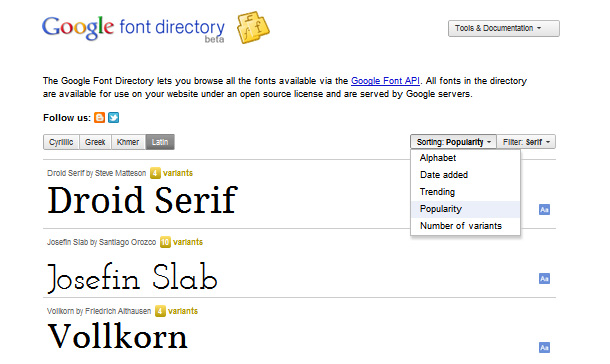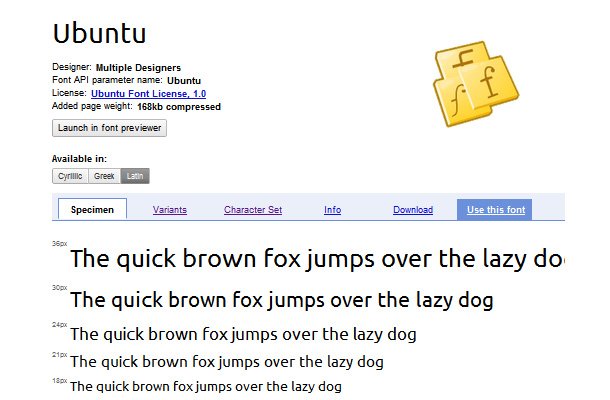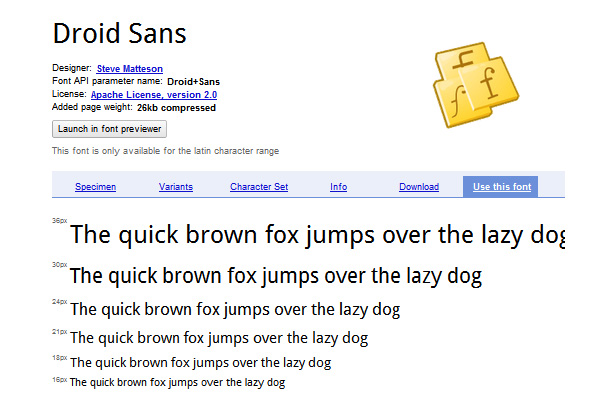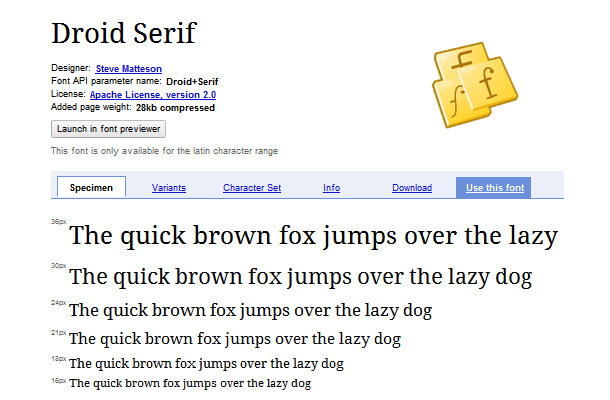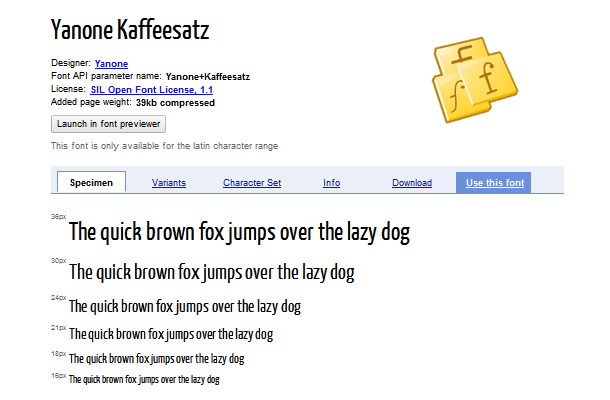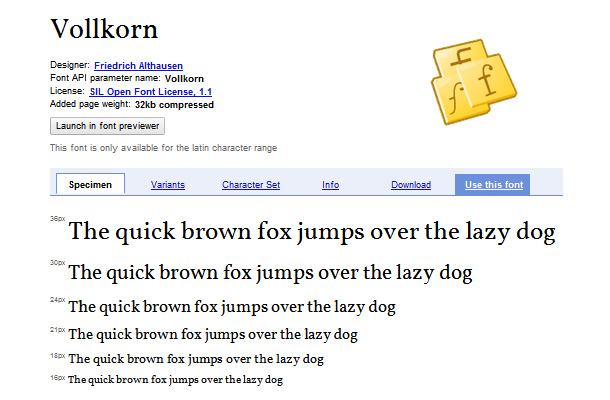
Die Google Web Fonts: Beliebte Schriften und praktische Tipps
Die Entwicklung der kostenlosen Web Fonts von Google geht schnell voran, und im Dezember sind noch einmal über 20 neue Schriften ins Font-Directory aufgenommen worden. Darunter einige sehr hochwertige Free-Fonts, z.B. die Ubuntu-Schriftfamilie. Und neben den neuen Schriften sind seit unserem letzten Artikel „Die kostenlosen Web Fonts der Google Font API nutzen“ auch noch einige neue Funktionen zum Sortieren der Schriften im Directory dazu gekommen. Zeit also für ein Update zu den praktischen Google Fonts.
1. Was sind Google Web Fonts?
Mit den Google Web Fonts hast du die Möglichkeit eine ganze Reihe von Schriften auf deiner Webseite zu nutzen, ohne dass du diese auf deinen eigenen Server hochladen oder über ein @font-face Kit (z.B. von Fontsquirrel) selbst aufwendig einbinden musst.
Du musst lediglich, die für dein Design benötigten Schriften und Schriftstile über einen Code-Schnipsel einbinden (hier die Erklärung zur Verwendung der Google Fonts). Sobald deine Webseite aufgerufen wird, werden die Schriften dann über den Google-Server geladen. Mit Hilfe des von Google und Typekit (dem derzeit größten Anbieter einer kostenpflichtigen Web Font Library) entwickelten Web Font Loader (einer JavaScript-Bibliothek) kannst das Ladeverhalten deiner Schriften sogar noch gezielter beeinflussen.
Ein großer Vorteil von Web Fonts, besonders im Vergleich zur Verwendung von Images, ist die so verbesserte Ladezeit. Außerdem können mit den Web Fonts eine viel breitere Vielzahl von Schriften unkompliziert genutzt werden, und auch moderne CSS3-Eigenschaften (wie text-shadow oder gradients) können verwendet werden.
2. Neue Features im Google Font Directory
Um die Schriften im Google Font Directory zu sortieren, gibt es inzwischen die neuen, praktischen Filter-Optionen.
Du kannst die Schriften zum einen nach den Schriftklassen Serif, Sans-serif, Display (dekorative Fonts, besonders für Logos oder Überschriften geeignet) und Handwriting filtern.
Daneben gibt es noch die Möglichkeiten die Web Fonts alphabetisch, nach Einstellungsdatum, Trend, Beliebtheit und Anzahl von Schrift-Varianten zu sortieren.
Eine zusätzliche Option ist das Filtern nach kyrillischen, griechischen, Khmer und lateinischen Schriften. Mit einem kleinen, blauen Symbol in der Schriften-Liste sind die zur Verfügung stehenden Schriften auch noch einmal markiert.
3. Die beliebtesten Google Web Fonts vorgestellt
Inzwischen sind schon eine ganze Reihe Web Fonts im Google Font Directory eingestellt. Daher möchte ich die beliebtesten Font hier etwas genauer vorstellen.
Ubuntu
– Die kostenlose Font-Familie des Open Source Betrieb-Systems Ubuntu.
Auch auf der Ubuntu-Webseite gibt es die Ubuntu-Schrift im Einsatz zu sehen.
The typeface is sans-serif, uses OpenType features and is manually hinted for clarity on desktop and mobile computing screens.
Ubuntu Font Family, Canonical und Dalton Maag
Seit Dezember 2010 kannst du auch die Ubuntu Schrift-Familie über die Google Font API nutzen. Ubuntu ist in den vier Varianten normal, italic, bold und bold italic verfügbar.
Droid Sans
– Eine beliebte serifenlose, fürs Web optimierte Schrift von Steve Matteson.
Droid Sans was designed with an upright stress, open forms and a neutral, yet friendly appearance.
Steve Matteson, Ascender Corp., in der Schriftbeschreibung von Droid Sans
Droid Sans ist die derzeit beliebteste Schrift der Google Web Fonts. Du kannst die Schrift in den Varianten normal und bold nutzen. Droid Sans ist extra für die Verwendung im Web entwickelt worden, und eignet sich besonders gut für Fließtexte.
Droid Serif
– Eine fürs Web optimierte, angenehm lesbare Serifen-Schrift designt von Steve Matterson.
The Droid Serif font family features a contemporary appearance and was designed for comfortable reading on screen.
Steve Matteson, Ascender Corp., in der Schriftbeschreibung von Droid Serif
Die Droid Serif gibt es in den Varianten normal, italic, bold und bold italic. Die angenehm lesbare Serifen-Schrift eignet sich besonders gut für Überschriften und Fließtexte von Webseiten.
Yanone Kaffeesatz
– Eine von Jan Gerner gestaltete Free-Font.
Its Bold is reminiscent of 1920s coffee house typography, while the rather thin fonts bridge the gap to present times.
Yanone, in der Beschreibung von Yanone Kaffeesatz
Yanone Kaffeesatz eignet sich meiner Ansicht nach besonders für Webseiten-Slogans oder größere Überschriften. Die Schrift gibt es in den font-weights 200, 300, 400 und 700.